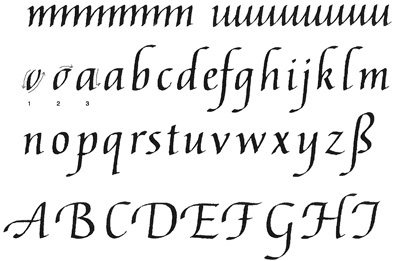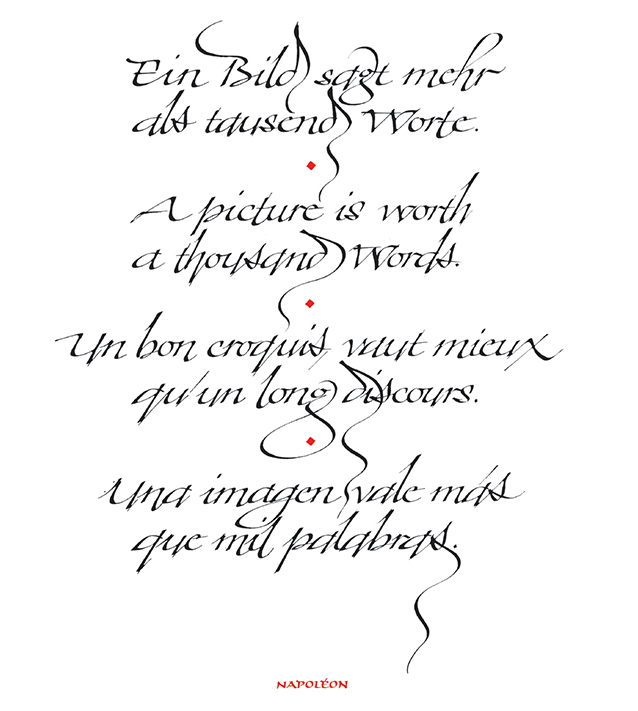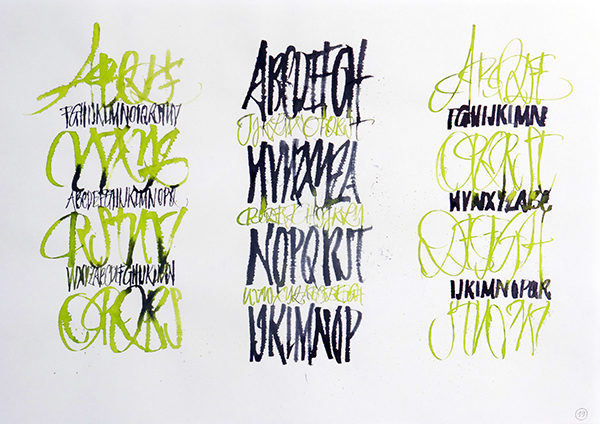
Die Ziehfeder als Instrument für Rhythmus und Komposition
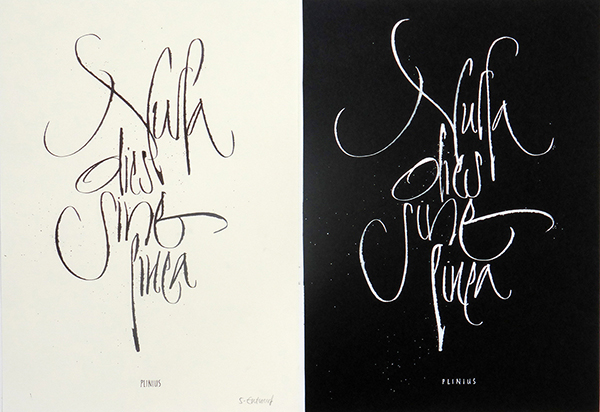
Kursbeschreibung: Die berühmte Ziehfeder (auch Reißfeder, engl. Ruling Pen), deren Nutzung für kalligrafische Zwecke in Wiesbaden ihre Ursprünge hat, kommt in diesem Kurs in vielfältigen Facetten zum Einsatz. Rhythmische Strukturen und Texturen dienen dem Einstieg ins Buchstabenformen. Anschließend werden wir auf die unterschiedlichen Möglichkeiten der Federmanipulation eingehen („1., 2. und 3. Gang“). Wir werden weiterhin ganz spezielle Übungen machen und viel experimentieren, um dieses nicht einfach zu handhabende Schreibinstrument kennen zu lernen. Alphabetische Kompositionsübungen werden genauso gemacht wie auf die Gestaltung von Worten und Texten eingegangen wird. Die Ziehfeder hat in Deutschland eine besondere Tradition, die bereits in mehreren Generationen "weitervererbt" wurde. Mehr dazu im Workshop!
Der Workshop richtet sich an Personen, die Erfahrung mit der Kalligrafie haben und die wichtigsten Grundschriften beherrschen.
Kalligrafie für Fortgeschrittene an der Sommerakademie 2026
Die englische Schreibschrift
Kursbeschreibung: Ein Intensivkurs! Die elegante englische Schreibschrift (frz. Anglaise, engl. Copperplate) ist in dieser Sommerakademie unser Hauptthema. Nach einer kurzen Wiederholung der Kleinbuchstaben und der einfacheren Großbuchstaben werden einige ihrer schönen Varianten gezeigt und geübt. Weitere zusätzliche Schwünge, Schleifen, Schlaufen und Schlenker (um nicht „Schnörkel" sagen zu müssen ;-) ! werden demonstriert und erlernt. Ein besonderer Fokus wird auf das Schreiben der englischen Schreibschrift in verschiedenen Größen gelegt. Wir werden uns dazu ein kleines Musterbüchlein / Leporello anlegen. Am Ende der Woche wird ein Blatt mit einem längeren Text stehen.
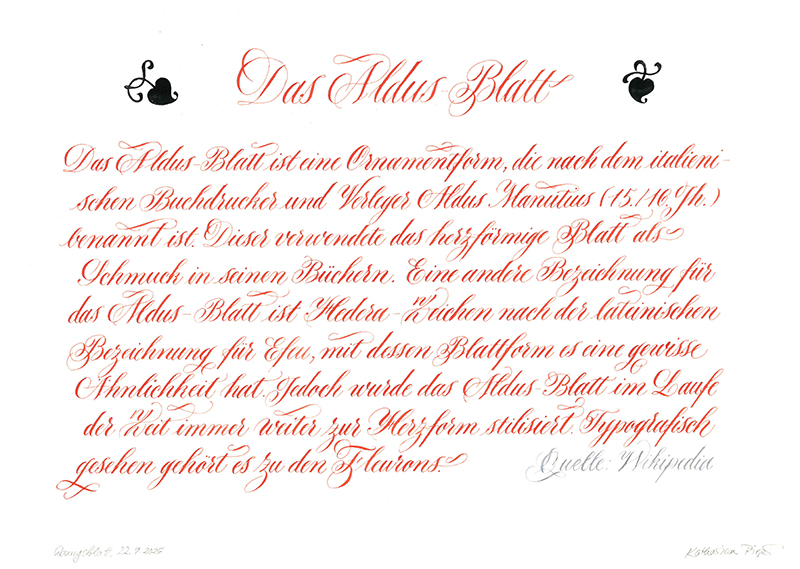
Offenes Atelier
Das offene Atelier dient der Vertiefung bereits erlernter Schriften. In ruhiger kalligrafischer Atmosphäre kann jeder, der bereits einen oder mehrere Kurse besucht hat, teilnehmen und erhält individuelle Hilfestellung.
Die englische Schreibschrift
Aufbaukurs
Dieser Kurs richtet sich an diejenigen, die bereits mehrere Workshops zur englischen Schreibschrift besucht haben. Klein- und Großbuchstaben werden vertieft und das Gestalten eines längeren Textes angegangen.
Civilité – von der schwungvollem mittelalterlichen Schrift zur Druckschrift
Aufbaukurs
Die Civilité ist eine gebrochene Schrift, die in Frankreich von dem Typografen Robert Granjon in Lyon um 1557 ursprünglich als Druckschrift geschaffen wurde. Sie bietet interessante Formen und viel Anregung zum Erweitern des Formrepertoires, denn sie zeichnet sich durch das Spannungsverhältnis zwischen niedrigen Kleinbuchstaben und sehr kalligrafischen, ja waghalsigen Schwüngen bei den Großbuchstaben aus. Das Alphabet hat Ähnlichkeiten
mit der Bastarda und wird sehr selten unterrichtet.
Humanistische Kursive für Einsteiger
Grundkurs/Aufbaukurs
Dieser Kurs ist sowohl ein Einstieg ins kalligrafische Schreiben, aber auch für diejenigen geeignet, die bereits Kurse zur humanistischen Kursive besucht haben. Klein- und Großbuchstaben, Wortgestaltung und einen kurzen Text schreiben sind Hauptthema